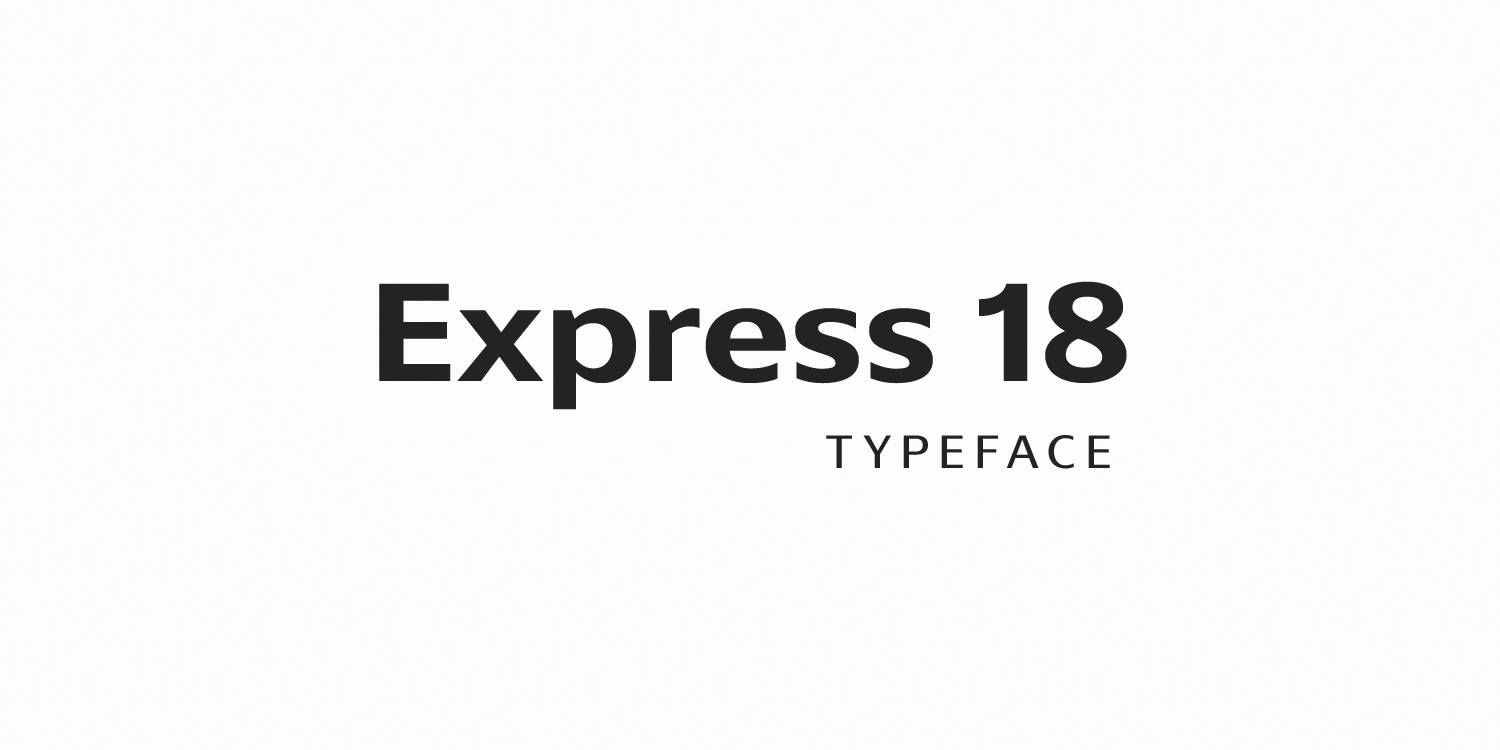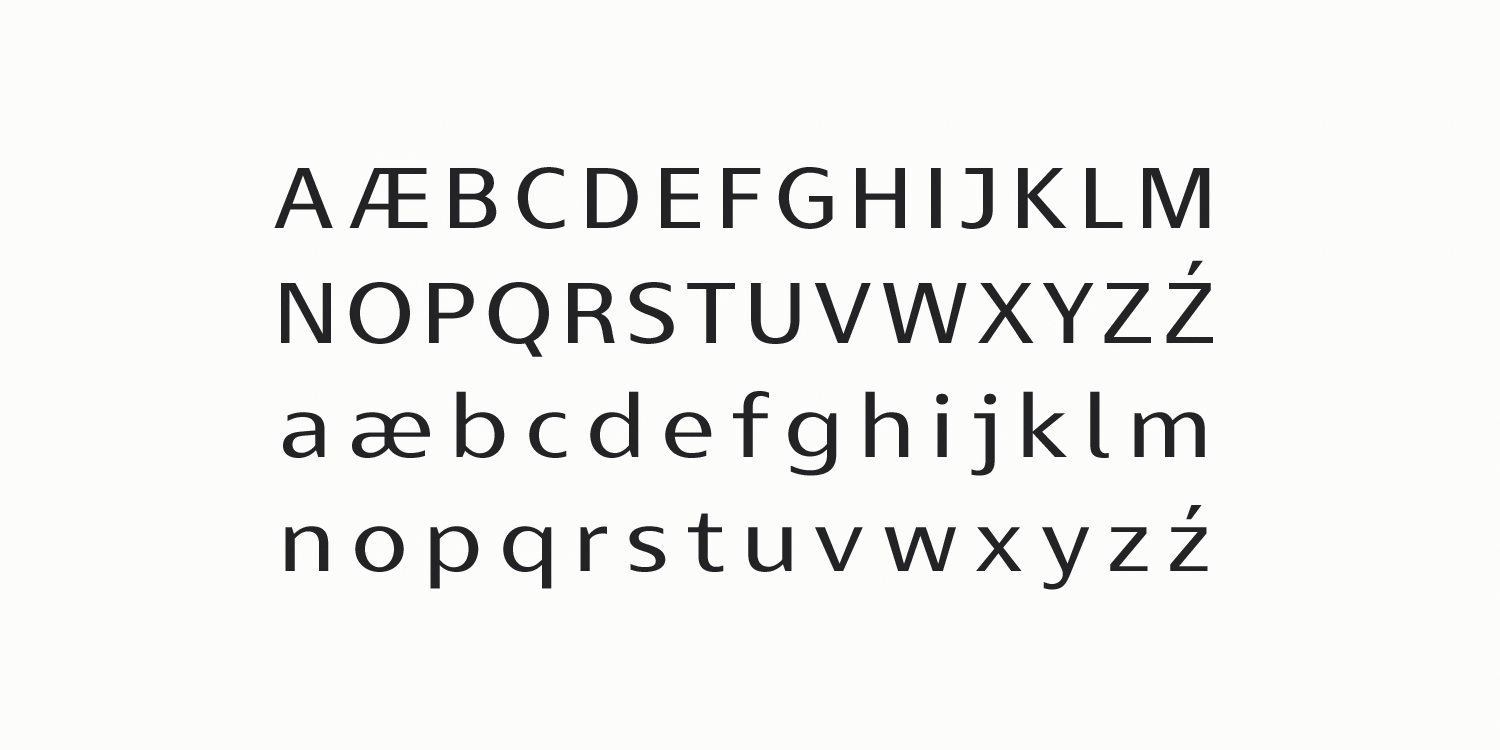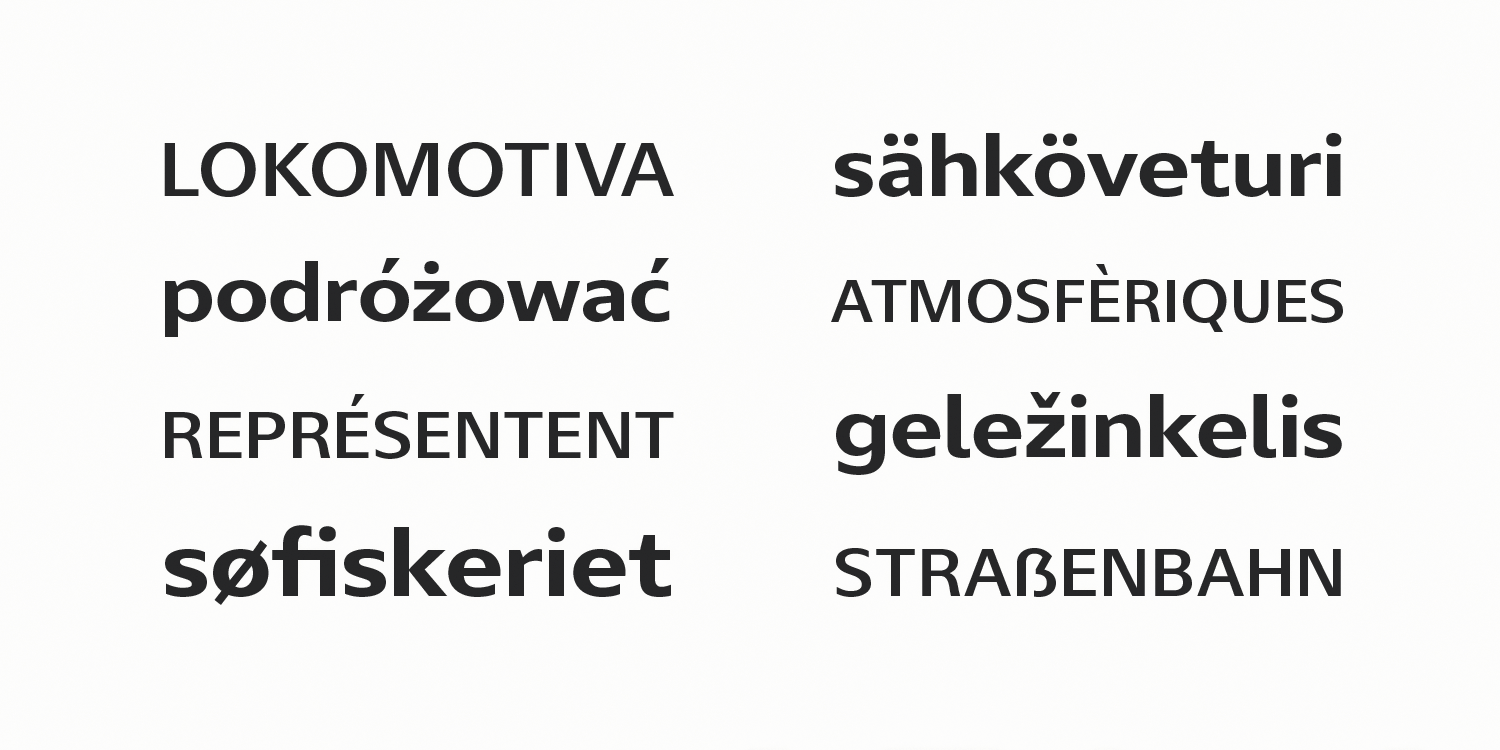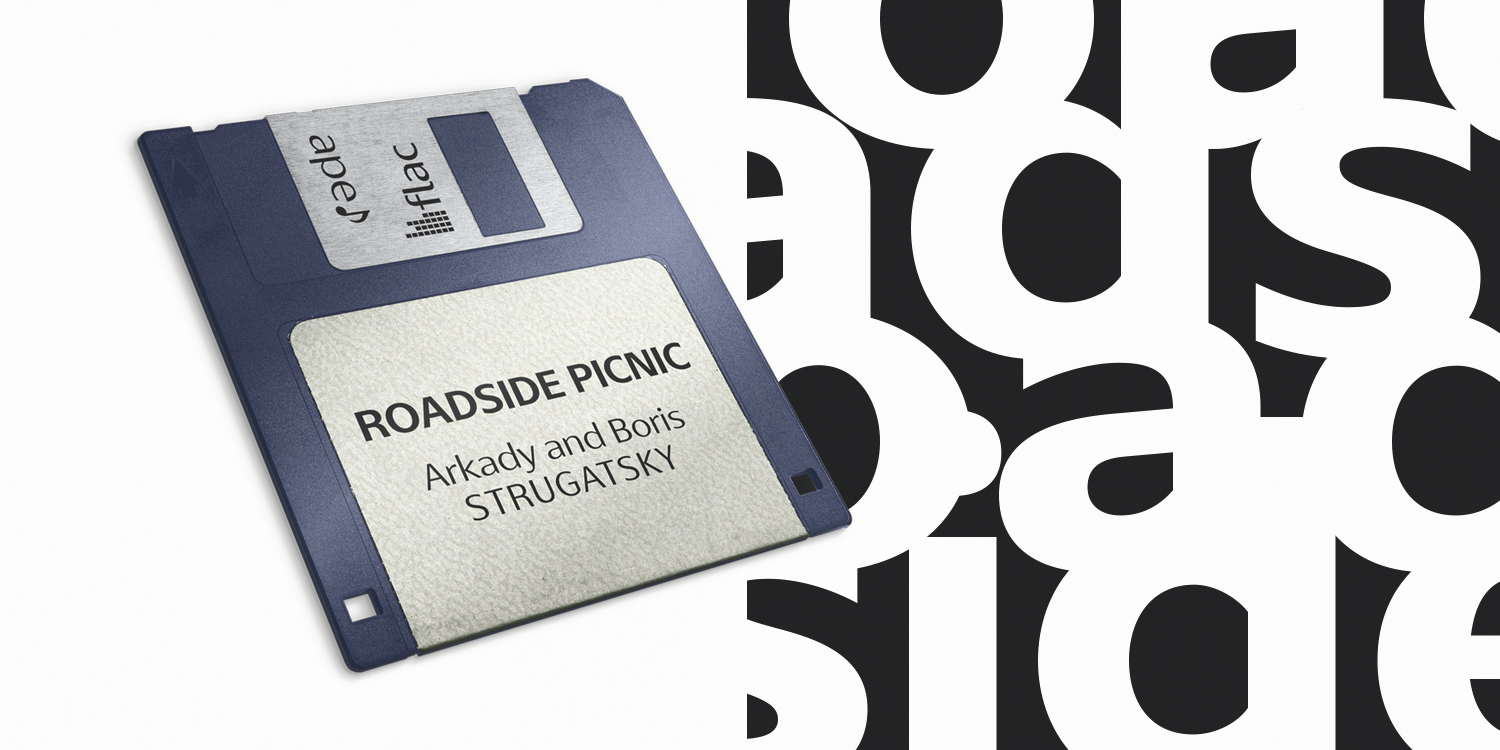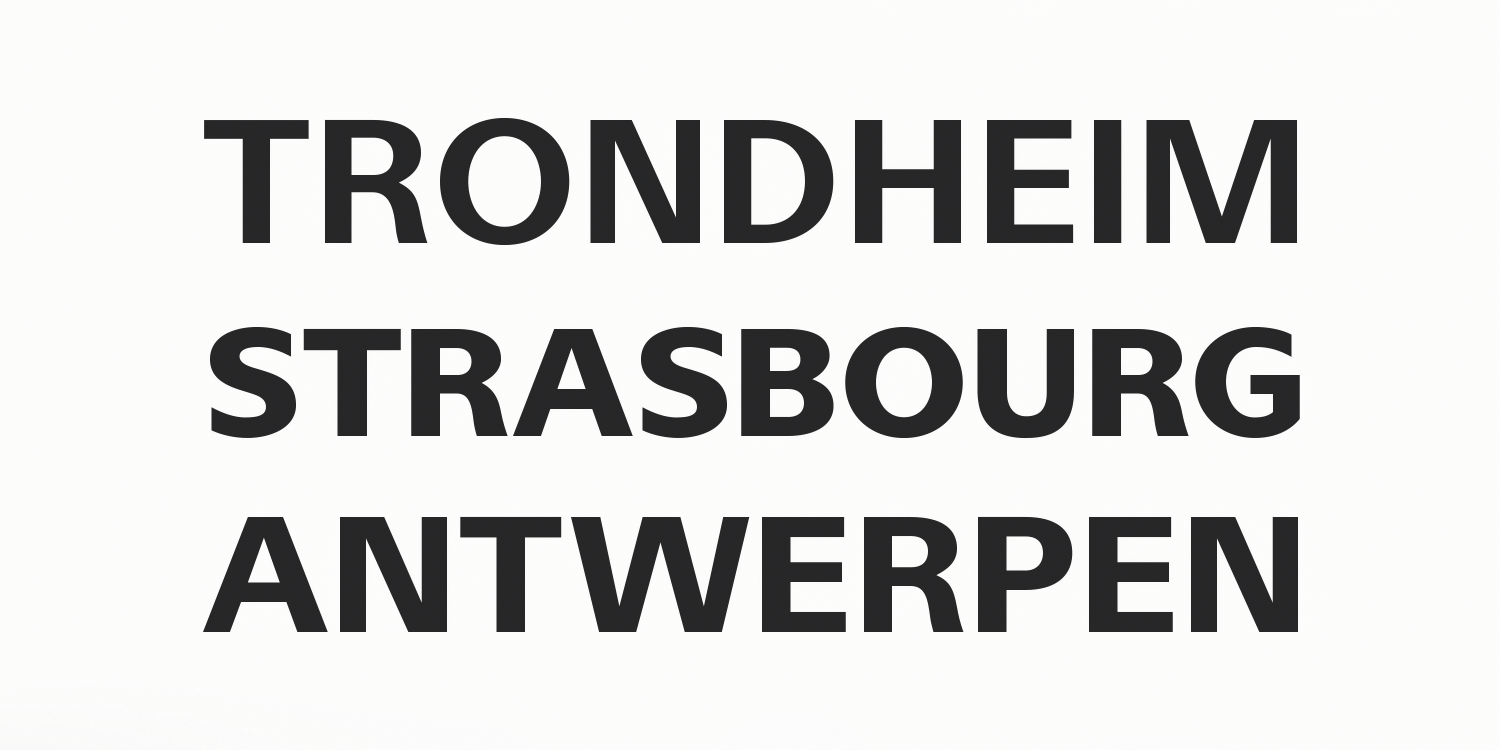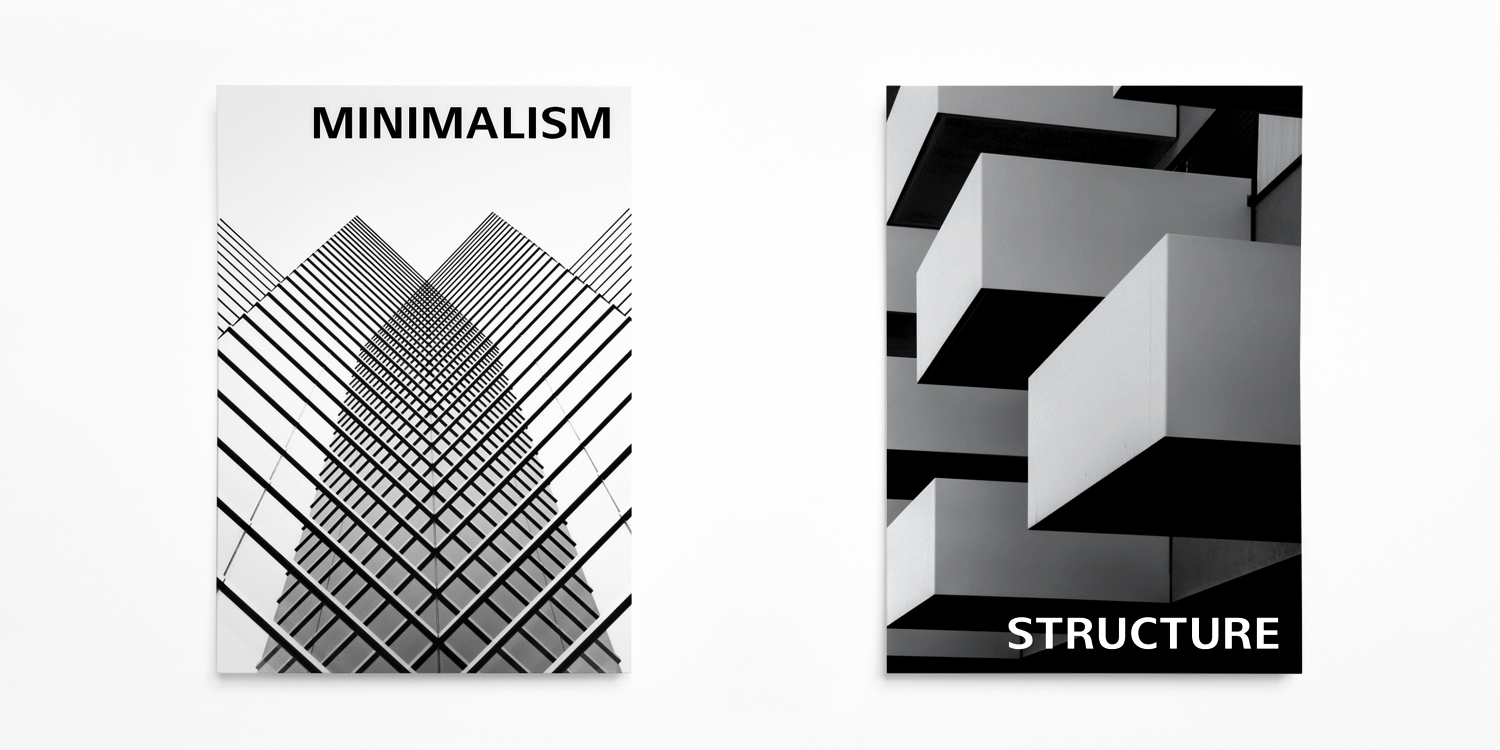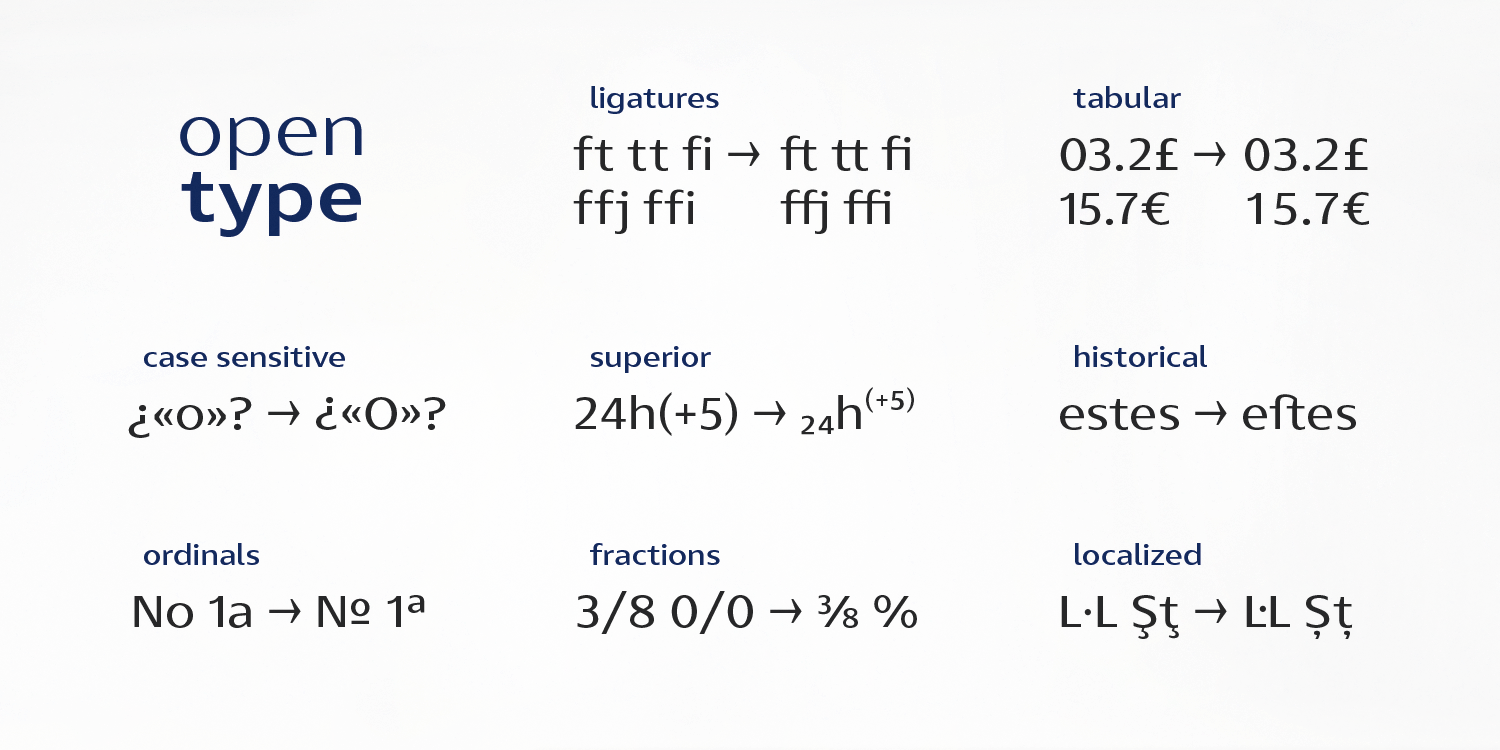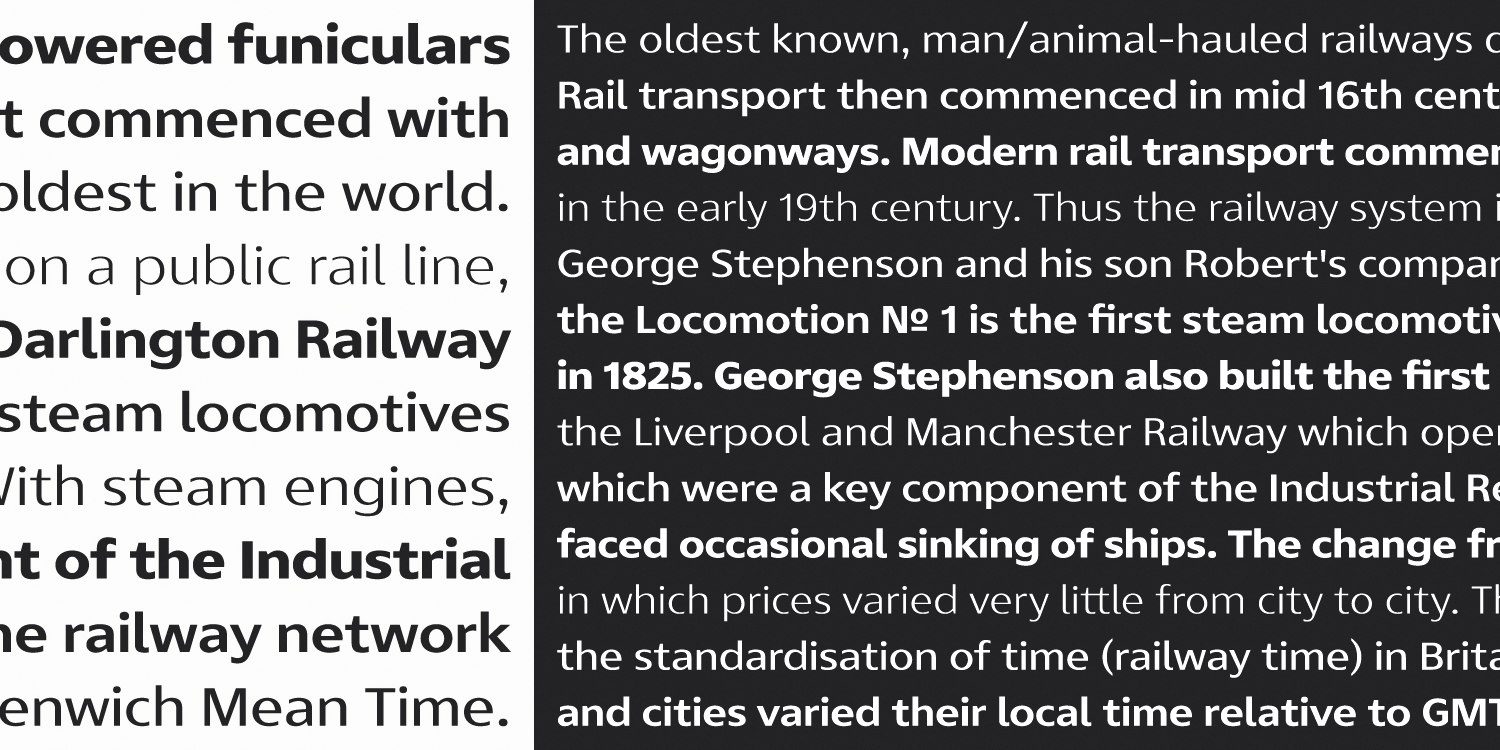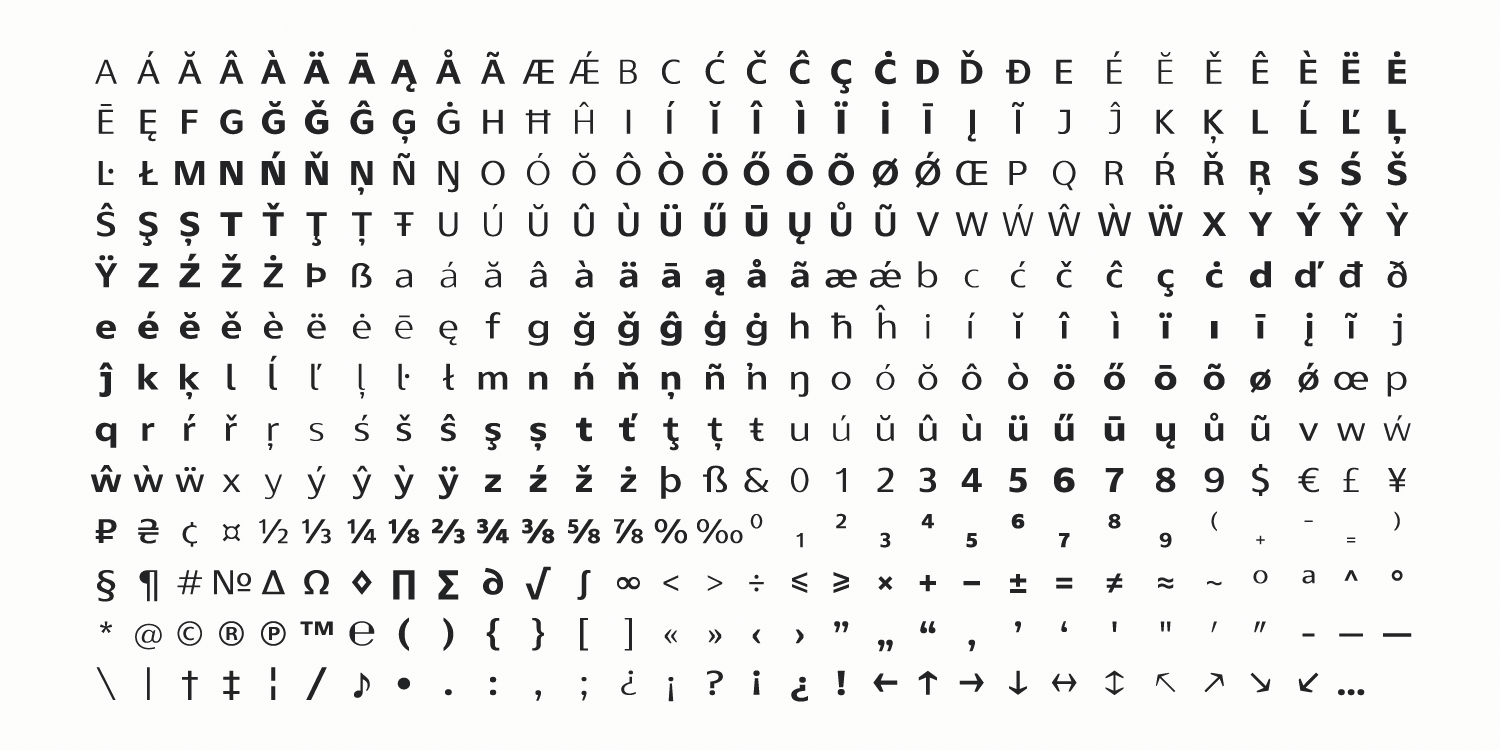
Express 18 | typeface
Express 18 — шрифт без засечек с открытыми формами и небольшим контрастом. Гарнитура состоит из 7-и различных начертаний, поддерживает расширенную латиницу и функции OpenType.
Разработан в 2020 году.
Шрифтовой дизайнер Игорь Косинский